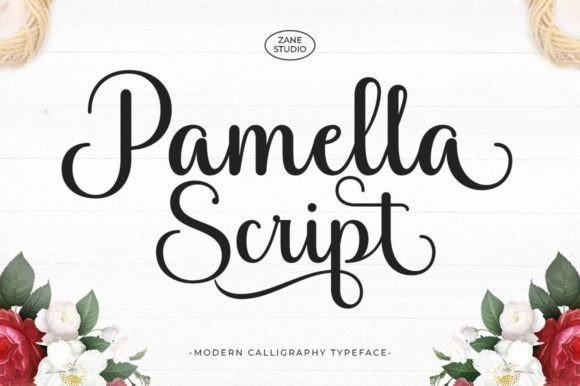
Pamella Script
適切なデザイン要素を見つけるのは難しい場合がありますが、Pamella Scriptは作品を即座に引き立てる優れたコレクションを提供します。
POD(オンデマンド印刷)製品、結婚式の招待状、またはソーシャルメディアのグラフィックを作成している場合でも、Pamella Scriptは理想的です。